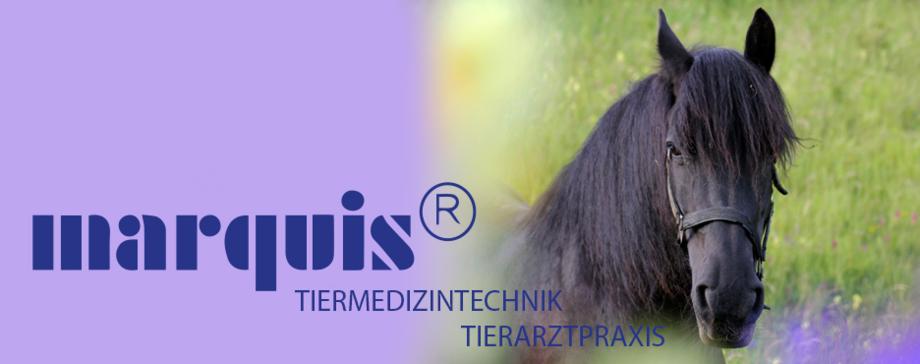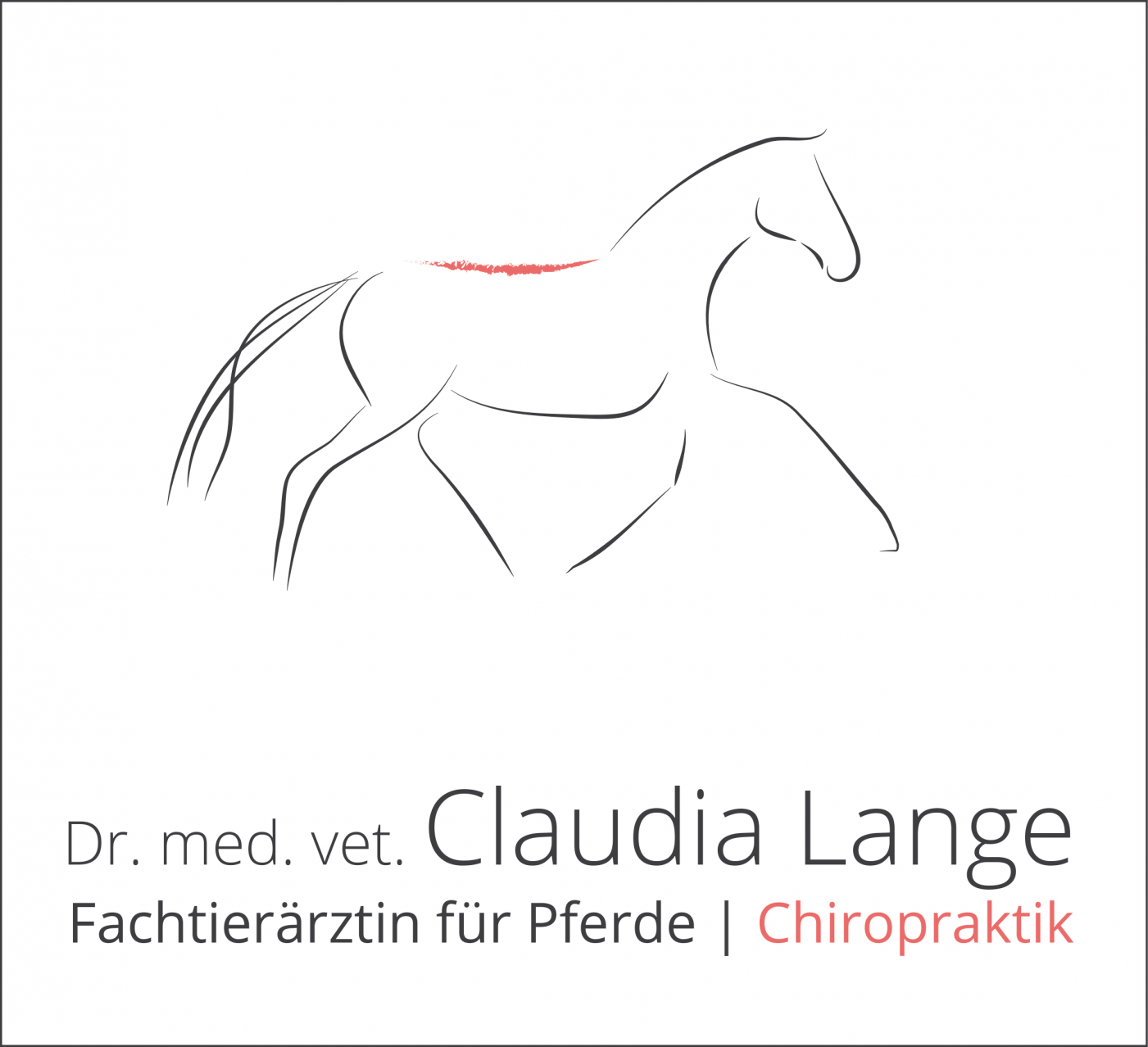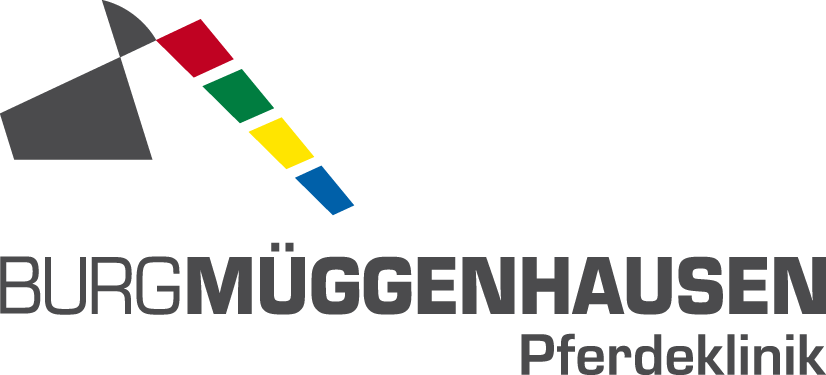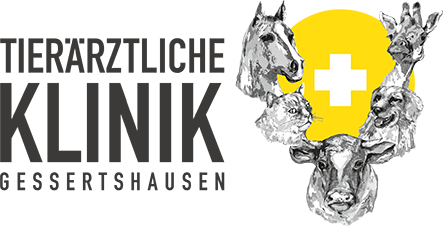
Schriftart für Tierarzt (speziallisierter Leistungssportpferde Orthopäde) mit High End Klientele
ich habe hier etwas mitgelesen und vor allem die Tips von Sebastian Nagel als sehr passend empfunden. Vielleicht könnt ihr auch mir helfen.
ich suche für unser Logo eine passende Schrift.
Wir sind eine Fahrpraxis, Orthopädie und Poor Performance bei Sportpferden mit mehrheitlich High End Klientele.
Ich suche eine Schriftart die Seriösität und Professionallismus austrahlt aber gleichzeitig auch edel, warm und ansprechend ist.
Keine sterile typische Tierklinikschrift...
wer hat eine Idee?
UND .... ich habe eine junge Grafikdesignerin, die wir persönlich kennen und die sich erst vor kurzem selbständig gemacht hat, mit jnserem Logo beauftragt. Sie macht das toll, jedoch bei der Schriftart habe ich 6 Vorschläge erhalten, wobei mir keiner zusagt. Und da ich sie nicht demoralisieren will, habe ich ihr gesagt ich würde mich mal umschauen und ihr einen Vorschlag senden, damit sie sehen kann in welche Richtung ich es haben möchte..... VOILÀ!!!
Kannst Du uns noch etwas helfen? Es gibt abertausende Schriftarten, da wären weitere Eckpunkte zum Eingrenzen hilfreich.
Zum Beispiel:
• Wie sieht der Rest der bisherigen (Logo)gestaltung aus? Gibt es eine Bildmarke? Dann sollte die gesuchte Schrift dazu formal harmonieren.
• Interessant wäre auch die sechs bisherigen Vorschläge zu sehen, um zu wissen, was Du nicht magst.
• Was meinst Du mit »sterile typische Tierklinikschrift« genau? Kannst Du uns Beispiele zeigen?
• Kannst Du in etwa sagen, welcher Schrifttyp Dir vorschwebt? Script? Antiqua? Grotesk?
Wie Robert schon schrieb, würde es uns und dich weiterbringen, wenn du die bisherigen Ergebnisse zeigst und vor allem deine Gedanken dazu: Was gefällt dir, was gefällt dir nicht, vielleicht sogar, warum dir dies oder jenes nicht gefällt. Dann finden sich hier viele, die gewohnt völlig ohne Polemik helfen.
Besteht das Logo nur aus Text? Oder ist eine Wort-Bild-Marke geplant, also eine feste Verbindung von Text und Bild oder Illustration? Gefällt dir eher das eine oder das andere? Warum?
Wenn es um Schrift geht, reicht es nicht zu sagen, daß sie nicht gefällt. Hier muß der Designer ggf. selbst die Vokabeln vorgeben, um ein Gespräch zu ermöglichen und zu ermitteln, was an der Schrift stört. Die Schrift ist in einen Entwurf eingearbeitet und oft nicht einfach austauschbar, deshalb ist es mir lieber, ich spreche mit Auftraggebern über einen Gesamteindruck, um das Problem zu erkennen und zu beheben. Wenn jemand beispielsweise mit dem Wunsch kommt, ich möge eine schöne Schreibschrift auf ein Briefpapier drucken und ich dann erfahre, daß die Briefe von Hand geschrieben werden sollen, werde ich sehr darauf hinweisen, daß die schöne Schreibschrift die an sich unauffällige Handschrift durch den Gegensatz lächerlich aussehen läßt. Es gehört also auch zur Designarbeit dazu, falsche Vorstellungen zu korrigieren. (In meiner »Stilkunde« gibt es übrigens eigens ein Kapitel »Mit Designern reden«.)